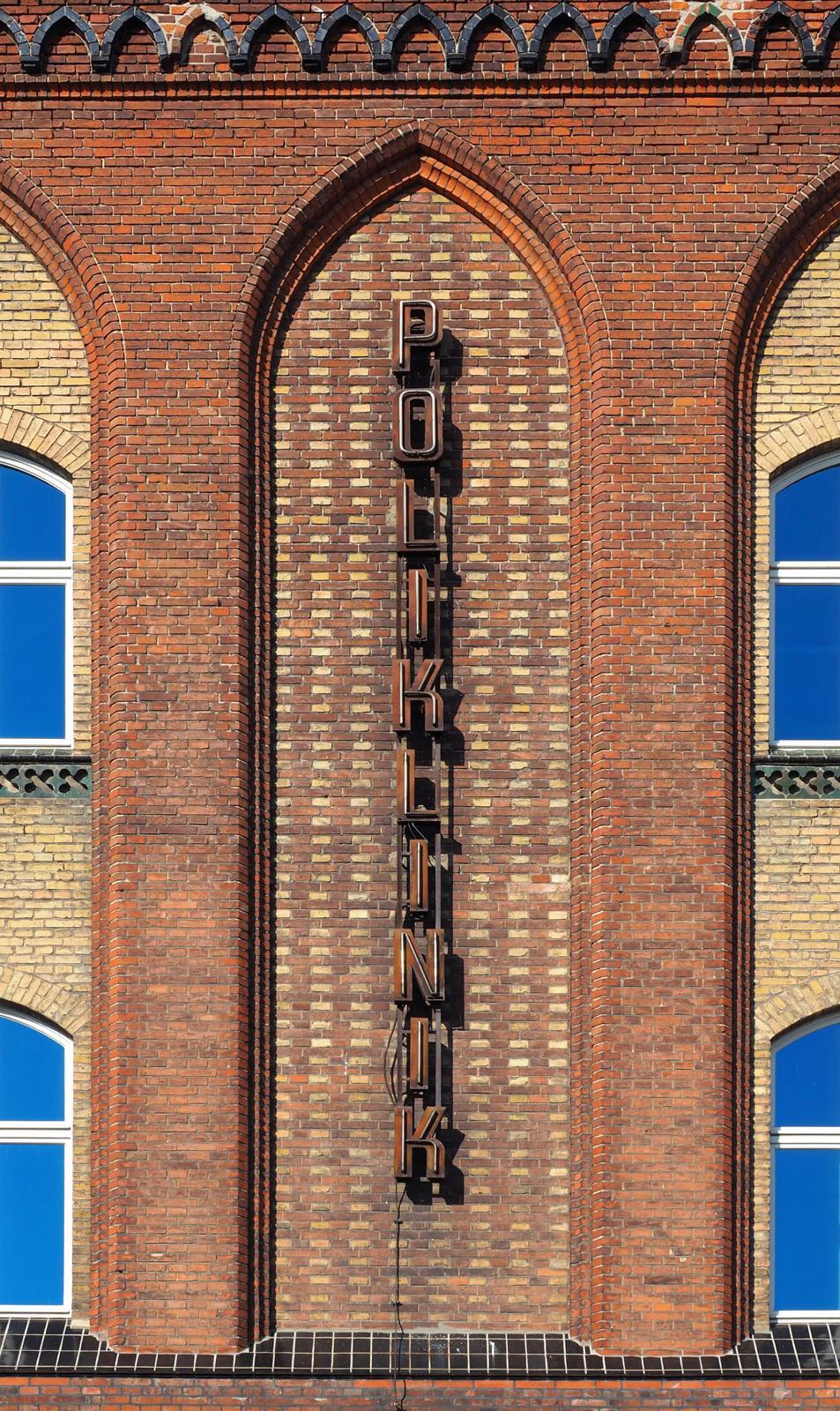
Leuchtreklame der 1950er DDR
Ich suche Informationen zu der Schriftfamilie einer großen Außenleuchtreklame aus den 1950er Jahren der DDR. Die besondere Form des "K" ist mir dabei gleich aufgestoßen. Diese weicht auch von den Übersichtsbildern der damaligen Literatur ab, die dort eher ähnlich der "Maxima" ausgebildet sind.
Bis in die 1990er Jahre hinein, waren Schriften mit Namen etwas für das Druckgewerbe. Alle anderen Berufe, die irgend etwas mit Schrift zu tun hatten, wie Schildermaler, KFZ-Lackierer, Steinmetze und eben Leuchtreklame-Hersteller mussten ihre Entwürfe noch selbst anfertigen, und Schriftgestaltung gehörte noch zur Ausbildung. Dazu gab es dann Lehrbücher wie dies hier beschriebene: